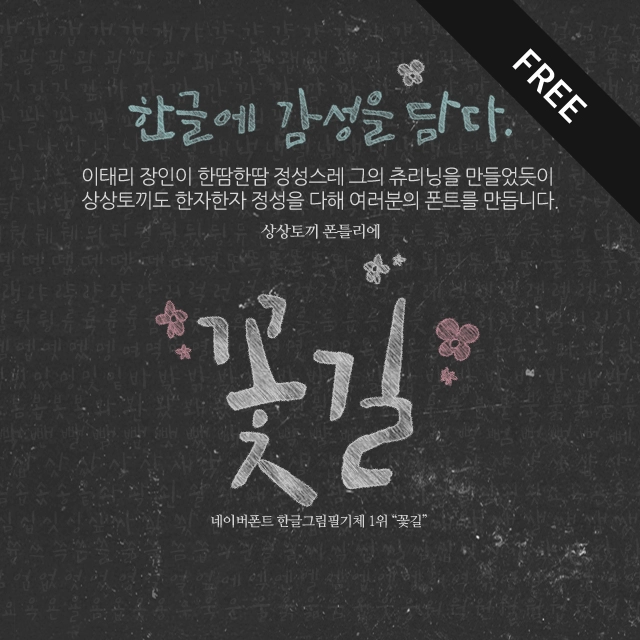
상상토끼 꽃길
사방간데 넘실데는 꽃길처럼 비단색으로 물든 감성 캘리그라피 서체, 꽃길
사방간데 꽃길 넘실대는 5월에 만들어진 감성 폰트 <꽃길>은 폰트를 만드는 캘리그래퍼로 불리는 상상토끼 용이 작가의 붓글씨를 기초로 해서 만들어진 폰트입니다. 소중한 글씨로 멋진 폰트를 만들어준 용이 작가에게 감사의 마음을 전합니다. |